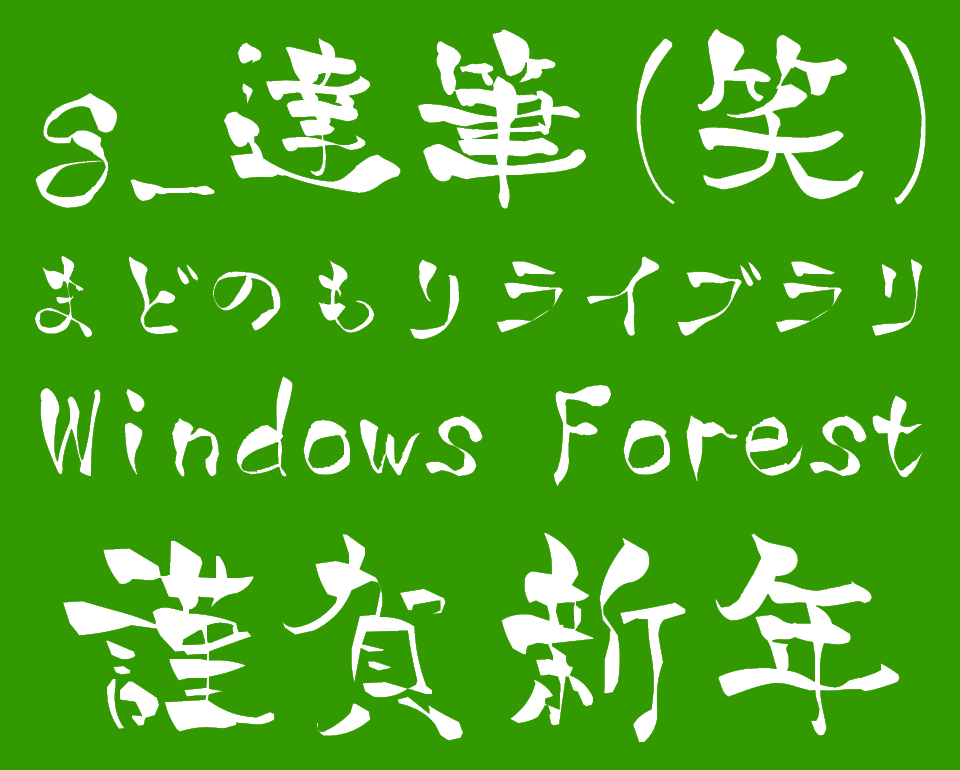
年賀状に最適! 古文書を思わせる手書き感が魅力な毛筆体フォント「g_達筆(笑)」
教育漢字に加えて年賀用の漢字を収録
「g_達筆(笑)」は、年賀状向けの毛筆体フォント。ひらがな、カタカナ、英数字、記号、1,006字の教育漢字に加えて、53字の年賀用漢字なども収録されている。
文字が全体的に揺らいでいたり、太さの使い分けが極端だったりと、毛筆特有の力強さや優美さに欠け、どこか頼りない手書き感。それでも、作者が自身の年賀状で使うためにしたためたとのことで、芸術性も垣間見える“へたうまさ”が特徴だ。
へたうま系の毛筆体と言えば、ポップでかわいらしい雰囲気のデザインが思い浮かぶ中、本フォントは古風な印象を受ける。それはちょうど、古文書や掛軸にありそうな文字の味わい。